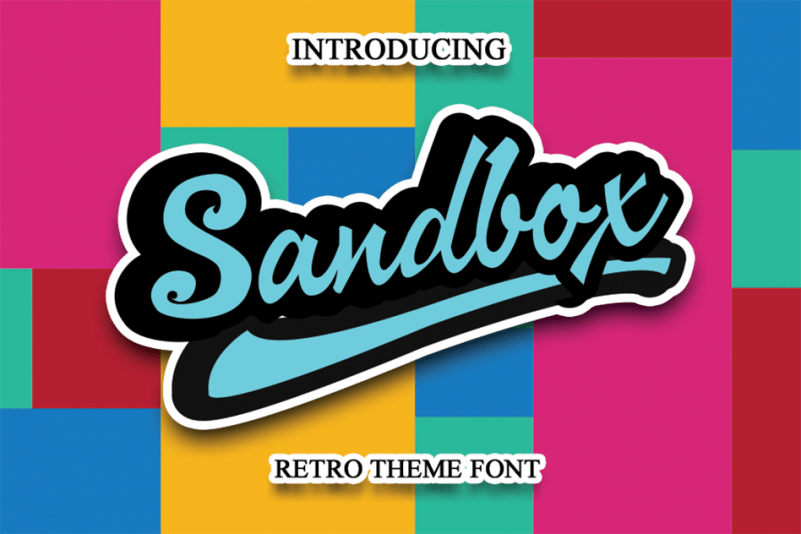
Sandbox Script Font – Fonte Grátis
Sandbox Script Font
Sandbox Script Font é uma elegante fonte cívilizada e em cauda que traz à tona um toque sofisticado para seus projetos de headlines e logotipos. Desenvolvida para dar um toque estiloso, essa fonte se destaca por sua força, confiança e dinamismo, tornando-a uma escolha óbvia para qualquer projeto que deseje adicionar um toque nostálgico às suas criações. Com seu estilo retrô e aveludado, o Sandbox Script Font é perfeito tanto para aplicar em cabeçalhos como em logotipos. Suas linhas finas e grossas combinam de forma suave com as letras mais elaboradas, criando um equilíbrio elegante que pode ser tanto usado para adicionar personalidade a qualquer design como para dar uma pausa nostálgica a projetos mais tradicionais. Este é um excelente recurso para designers que querem adicionar um toque de nostalgia e sofisticação sem comprometer o estilo contemporâneo. Sua consistência e legibilidade garantem que seja uma escolha conveniente tanto para designers gráficos quanto para web, permitindo que você faça a diferença em qualquer projeto com apenas uma fonte.